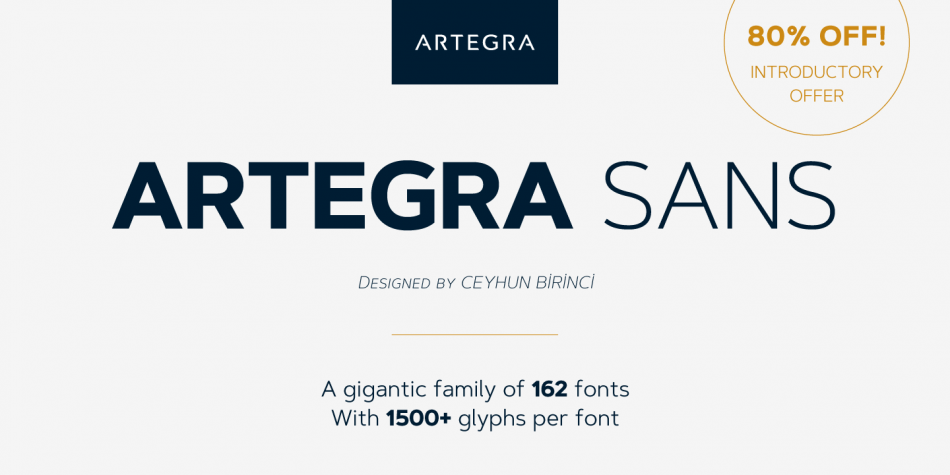
Derzeit gibt es bei MightyDeals die Latina (Latinotype, Rodrigo Fuenzalida) for $19. 11 Stärken, jeweils aufrecht und kursiv. Ist jetzt nicht so extrem ungewöhnlich, aber die Kursive hat es mir persönlich angetan.
Die Favela ist eine neue Grotesk mit Small Capitals und SC-Versal-Eszett. Das Besondere an ihr ist, dass die ganz dünnen Schnitte auch sehr eng laufen, »normale« Schnitte haben eine normale Breite und die fetten Schnitte sind dann »extended« ausgeführt. Das wirkt aber für mich, jedenfalls bei den fetten Schnitten, doch relativ organisch. Zur Zeit gibt es die 18 Schnitte zum Einführungspreis von knapp 40 Euro bei MyFonts: https://www.myfonts.com/fonts/borutta/favela/
Danke für den Tipp! Leider scheinen die Schnitte ziemlich zusammengewürfelt worden zu sein. Heavy und Bold unterscheiden sich z.B. in mehreren Details, darunter die ß-Form und die ungarischen Diakritika. Die ẞ-Form ist m.E. ziemlich gewöhnungsbedürftig und kaum alltagstauglich. (Geht sie etwa auf Renner zurück? :-?)
Ach ja: das wichtigste Ausschlusskriterium für mich ist, dass die Schnitte (wenn man der Myfonts-Website) glauben darf, keine dieser abgefahrenen Ligaturen mitbringt (z.B. ft, das wie ein rundes A aussieht).
(Das ẞ lässt sich anscheinend nur in der Linotype-Vorschau bewundern.)
Und derzeit als Einführungsangebot bei Linotype die Camila (mit Versal-Eszett) in 13 Schnitten (Thin, Light, Regular, Medium, SemiBold, Bold und Black, wobei die Regular anscheinend nur als Italic dabei ist) für 56,84 Euro:https://www.linotype.com/de/5367814/camila-complete-family-pack-product.html?utm_source=LinoLetter&utm_campaign=05711a2e34-Special+NL-17-01-DE+Latinotype&utm_medium=email&utm_term=0_c5843cdb9f-05711a2e34-28413901
Neue Kabel und noch 2 andere Familien zum Sonderpreis bei Linotype
Bei Fontspring ist die Ategra Sans im Angebot: 54 Schnitte für 115 $ (und kleinere Pakete)
Auf den ersten Blick scheint die durchaus Brauchbar zu sein. Was meint ihr?
eine sehr nette handschriftliche (aus wien!) bestehend aus 18 fonts mit vielen OT features (aber leider ohne versal-eszett) gibt’s bis 13. april um heiße 17 euro 40.
Ob sich das lohnt - dazu würde ich von Euch Experten gern mal eine Meinung hören.
Außerdem bietet Linotype aktuell u. a. die neue Caecilia Sans Text befristet an. Auch dazu: Lohnt das? Solche neutralen Schriften gibt's inzw. ja zuhauf.